前回に続き、横浜市内の文字調査をレポートします。後半となる今回は駅の案内サインを中心にレポートします。
1. 横浜駅連絡通路の案内サイン。和文には新ゴ、欧文にはRotis(混植用の欧文はHelvetica)が使われている。
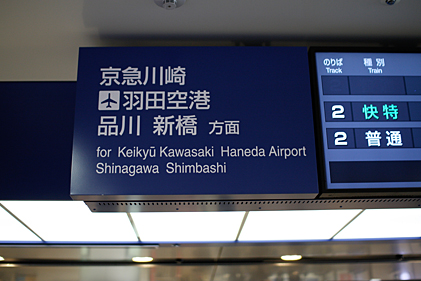
2. 京急線の出発時刻案内。和文には新ゴ、欧文にはHelveticaが使われている。
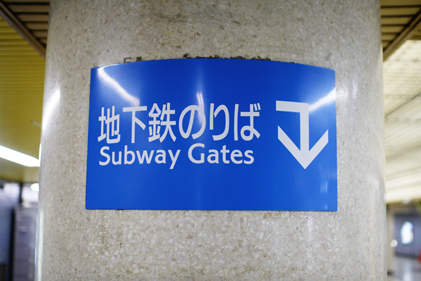
3. 横浜市営地下鉄の案内サイン。和文にはナウ、欧文には Corinthianが使われている。CorinthianはJohnston sansやGill sansと同じ系譜の書体。
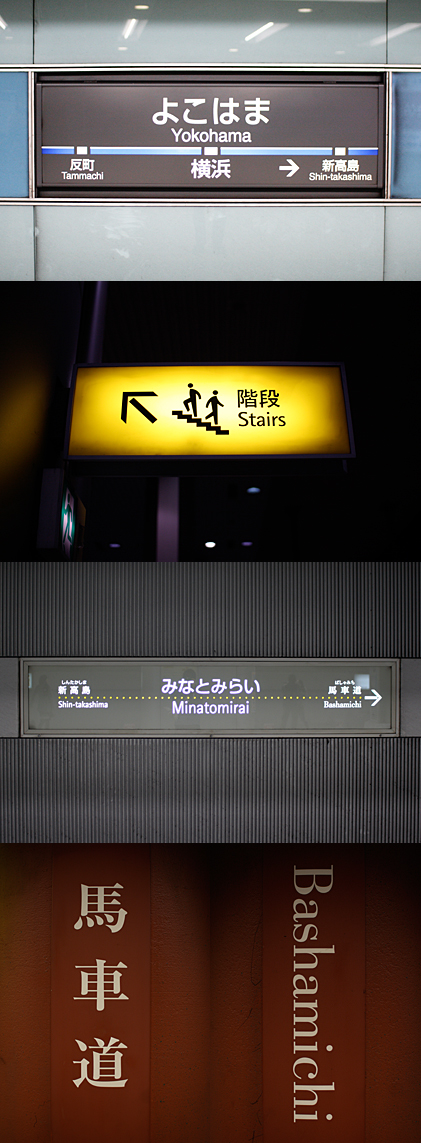
4. みなとみらい線は駅ごとに建築様式を分け、それに歩調を合わせる形で書体も振り分けている。基本書体は和文に新ゴ、欧文にRotisだが、馬車道駅では和文にリュウミン、欧文にBodoniを使用している。
横浜市営地下鉄に使われている欧文書体にはすこし驚きました。横浜市にある他の鉄道を見てもHelveticaやFrutiger、Rotisといったどちらかというと無機質な書体が選ばれているのに対し、どこか人間味が感じられる書体、Corinthianが使われているからです。書体だけで比べてみると横浜市営地下鉄が他の鉄道に比べて強い個性を放っているように感じられました。